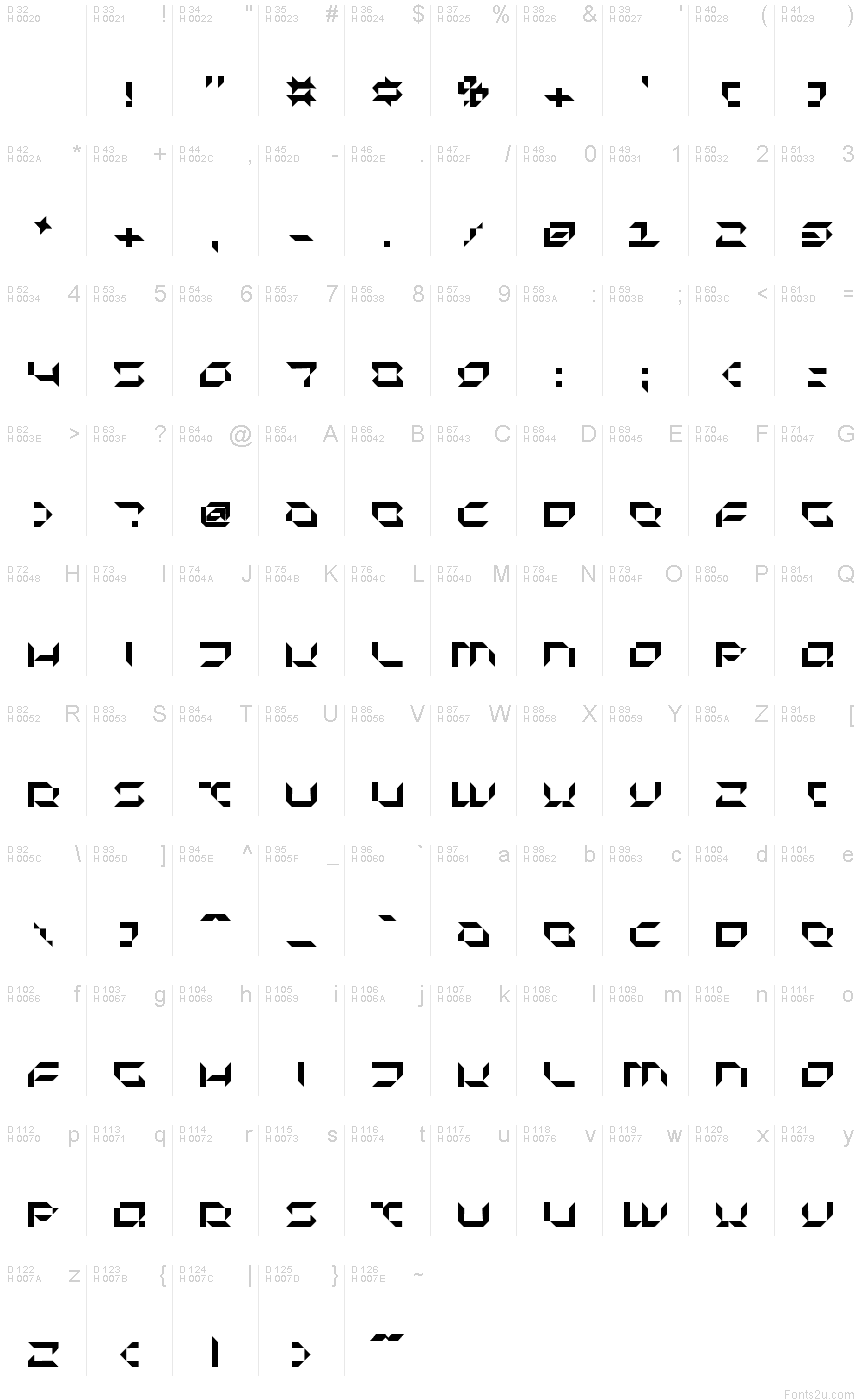
Pluranon, autorstwa Milana Zrnica i Tommy'ego Cary'ego, to darmowy, futurystyczny krój pisma typu display (tylko wielkie litery), zbudowany z blokowych, czarnych kształtów i ostrych, ukośnych cięć. Litery sprawiają wrażenie modularnych, rysowanych maszynowo, z przyciętymi rogami, dzielonymi formami i ciasnym, kanciastym rytmem, który nadaje alfabetowi surowy, sci-fi charakter.
Ten darmowy font idealnie nadaje się do plakatów, okładek albumów, grafik w grach, brandingu technologicznego, plansz tytułowych i krótkich nagłówków, gdzie litery działają równie mocno jako obiekty graficzne, co słowa. Świetnie sprawdza się również w logo i monogramach, ponieważ segmentowa geometria sprawia, że nawet krótkie frazy wydają się zwarte i architektoniczne.